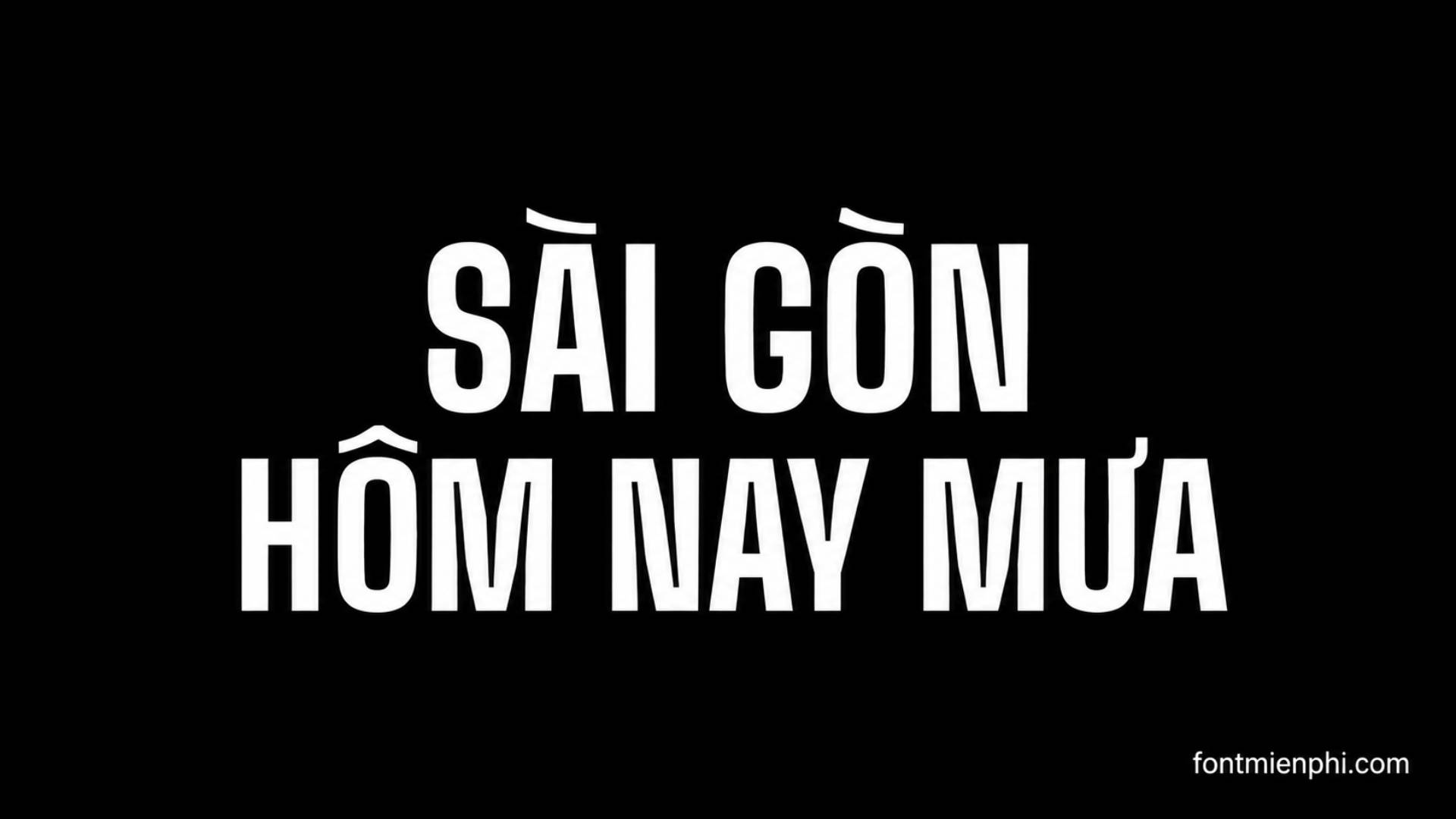
Tải Font Việt Hóa PS Big Shoulders – Nét Chữ Cao Khỏe, Đậm Chất Hiện Đại
Trong thế giới thiết kế đồ họa, việc tìm kiếm một phông chữ tiêu đề (Display Font) vừa mạnh mẽ, vừa tiết kiệm không gian ngang nhưng vẫn giữ được độ sắc nét không phải là điều dễ dàng. Font Việt hóa PS Big Shoulders xuất hiện như một giải pháp hoàn hảo cho những nhà thiết kế đang tìm kiếm sự đột phá. Với thiết kế vươn cao, vững chãi đúng như tên gọi “đôi vai rộng”, bộ font này mang đến sự chú ý tuyệt đối cho mọi ấn phẩm truyền thông.
1. Giới thiệu về Font PS Big Shoulders
Big Shoulders ban đầu là một dự án phông chữ mã nguồn mở (Google Fonts) được sáng tạo bởi nhà thiết kế Patric King. Điểm đặc biệt của Big Shoulders là nó được xây dựng dưới dạng Superfamily (siêu họ chữ) với nhiều phiên bản biến thể khác nhau về độ dày và chiều rộng, phục vụ tối đa cho các nhu cầu hiển thị đa dạng.
Cấu trúc của Big Shoulders thuộc dạng Condensed (thuôn hẹp) nhưng lại có chiều cao x-height lớn, tạo ra một hình thái hình chữ nhật đứng cực kỳ ấn tượng. Các đường nét được gọt giũa dứt khoát, mang đậm hơi thở của đô thị hiện đại, công nghệ và thể thao.
Phiên bản PS Big Shoulders Việt hóa đã được xử lý lại toàn bộ hệ thống dấu câu tiếng Việt, đảm bảo sự đồng bộ về mặt thẩm mỹ và khoảng cách (kerning) khi gõ văn bản, giúp các designer Việt yên tâm sử dụng trong mọi ngữ cảnh.
2. Đặc điểm nổi bật của Font PS Big Shoulders Việt Hóa
Bộ font này mang trong mình những ưu điểm vượt trội khiến nó trở thành “con cưng” của nhiều chuyên gia thiết kế UI/UX và đồ họa quảng cáo:
• Tối ưu không gian cực tốt: Nhờ form dáng hẹp chiều ngang, bạn có thể dễ dàng chèn những dòng tiêu đề dài vào các không gian giới hạn (như banner dọc, màn hình điện thoại di động) mà chữ vẫn to, rõ ràng và không bị ép méo mó.
• Đa dạng về trọng lượng (Weights): Cung cấp nhiều định dạng từ mỏng (Thin) đến cực dày (Black), giúp bạn linh hoạt tạo ra sự tương phản và phân cấp thông tin trong cùng một bản thiết kế.
• Phong cách dứt khoát, thể thao: Các nét chữ cứng cáp, góc cạnh tạo ra cảm giác năng động, tốc độ và tràn đầy năng lượng.
• Việt hóa chuẩn xác: Các dấu câu tiếng Việt được thiết kế khéo léo để không làm phá vỡ cấu trúc hẹp của chữ gốc, không xảy ra tình trạng lỗi hiển thị trên các phần mềm như Adobe Illustrator, Photoshop hay Figma.
3. Ứng dụng thực tế của Font PS Big Shoulders
Với ngoại hình cá tính và “cơ bắp”, PS Big Shoulders là sự lựa chọn không thể tuyệt vời hơn cho các dự án cần sự mạnh mẽ và hiện đại:
Mẹo thiết kế: Big Shoulders sinh ra là để làm tiêu đề. Hãy kết hợp nó cùng với một phông chữ Sans-serif có tỷ lệ tròn trịa hơn (ví dụ: Montserrat hoặc Roboto) cho phần nội dung (Body text) để tạo ra sự cân bằng hoàn hảo cho thị giác.
• Thiết kế Thể thao (Sports Design): Làm poster giải đấu, áo thun (typography streetwear), banner câu lạc bộ, phòng gym.
• Giao diện Website & App (UI/UX): Sử dụng làm font chữ cho Hero Section, Heading 1 (H1), hoặc các con số thống kê lớn trên Dashboard.
• Thiết kế Bao bì (Packaging): Rất phù hợp cho các sản phẩm công nghệ, đồ uống năng lượng, hoặc thực phẩm chức năng dành cho nam giới.
• Ấn phẩm sự kiện âm nhạc: Thể hiện tốt tinh thần sôi động của các sự kiện EDM, Rap, Hip-hop.